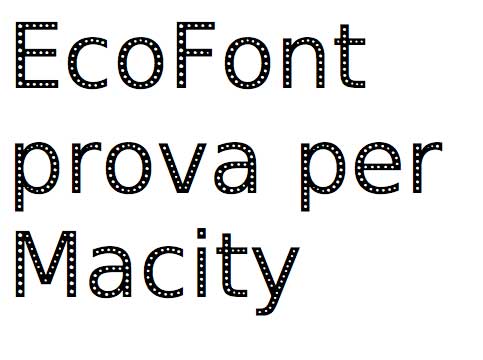
Scherzo, abile manovra di marketing o provocazione? E’ tutto quello che ci viene in mente apprendendo la notizia di una società olandese che ha rilasciato un font gratuito ribattezzato “Ecofont” grazie al quale dovrebbe essere possibile risparmiare toner o l’inchiostro delle cartucce della stampante.
I caratteri che compongo questo font (una variante di “Vera Sans”) sono composti da parti unite tra loro (punti di raccordo) da buchi bianchi. La presenza dei fori dovrebbe rendere possibile – a detta degli autori – “risparmiare fino al 20% di toner rispetto alla stessa pagina stampata con font tradizionali”. Il carattere rende bene se usato nelle dimensioni di 9 o 10 punti ed è una semplice alternativa a Verdana o altri font senza grazie.